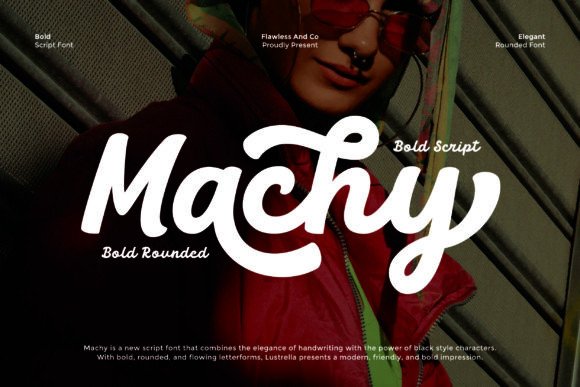
Machy
適切なデザイン要素を見つけるのは難しい場合がありますが、Machyは作品を即座に引き立てる優れたコレクションを提供します。
精密に作られたMachyは、クリーンなベクター、滑らかなタイポグラフィ、そして安心のための商用ライセンスを提供します。
POD(オンデマンド印刷)製品、結婚式の招待状、またはソーシャルメディアのグラフィックを作成している場合でも、Machyは理想的です。